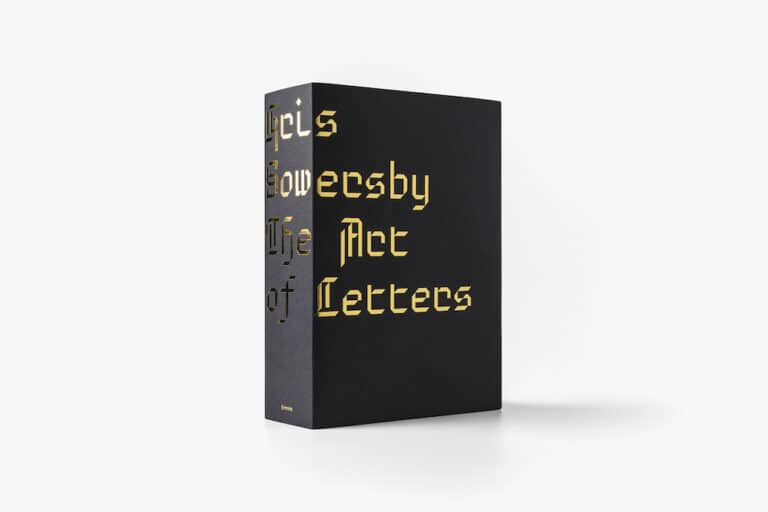
Typobuch: Lettern als Kunst
Die Schönheit von Einzelbuchstaben abseits ihres Verwendungskontexts verdeutlicht das Buch »Kris Sowersby: The Art of Letters«.
Die Arbeitsweise des neuseeländischen Typedesigners Kris Sowersby, Gründer der Foundry Klim Type, untersucht das Buch »The Art of Letters« von Mark Gowing und Dave Foster. Bestimmt wird es von der Idee, dass jedes Zeichen – entfernt man den Kontext von Sprachsystemen und Alphabeten – zu einem eigenständigen Kunstwerk wird. Eigens für den 800-seitigen Wälzer (Formist Editions, 90 US-Dollar, ISBN 978- 0-6485963-4-9) entwickelten Sowersby und Gowing einen von mittelalterlichen Buchschriften inspirierten Custom Font: Brotunda.